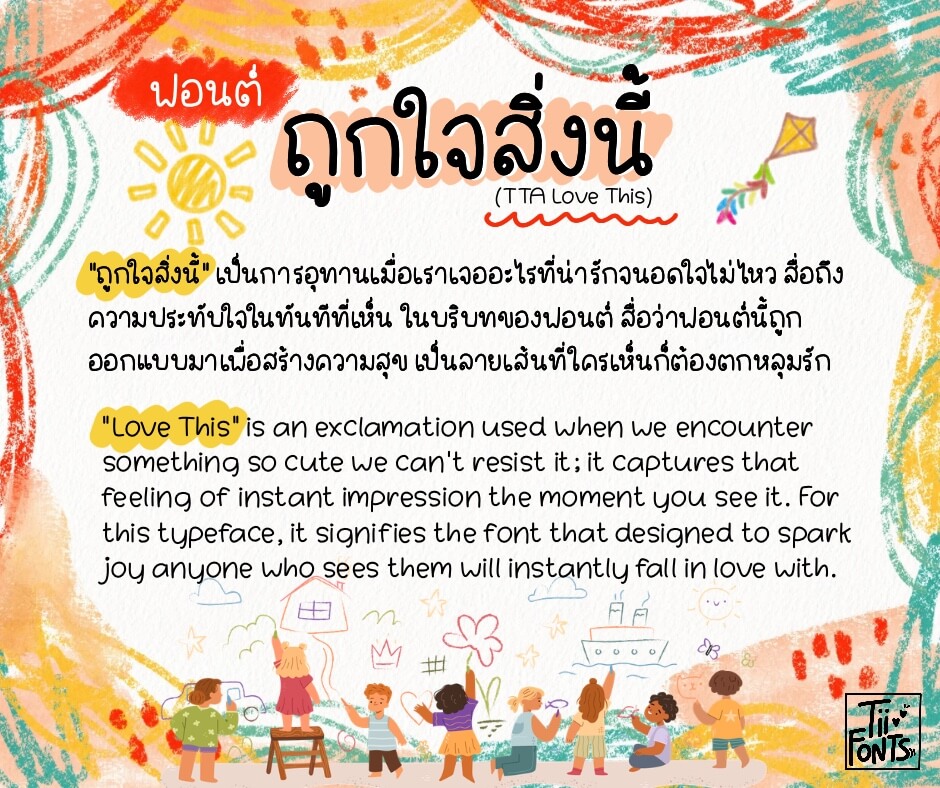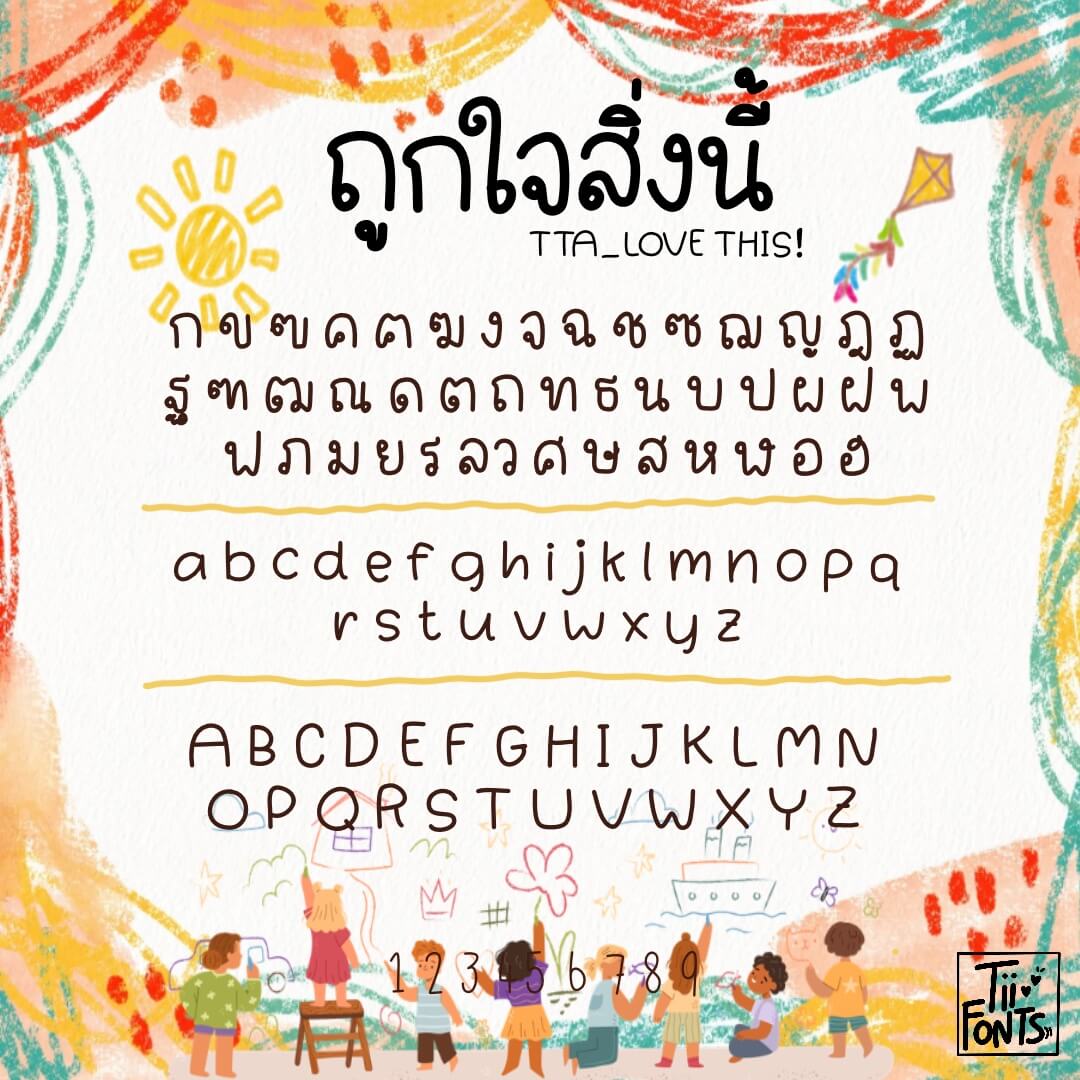
ถูกใจสิ่งนี้ (TTA LOVE THIS!)
พิมพ์ตรงไหนก็น่ารัก! กับฟอนต์ใหม่ “ถูกใจสิ่งนี้” ดีไซน์ลายมือสุดนุ่มฟู ให้ฟีลอบอุ่นและเป็นกันเองแบบ 10/10 ลายเส้นอ่านง่ายสบายตาสุดๆ ใครมองหาฟอนต์ที่ใช้แล้วงานดูมีชีวิตชีวา… ต้องฟอนต์นี้เลย